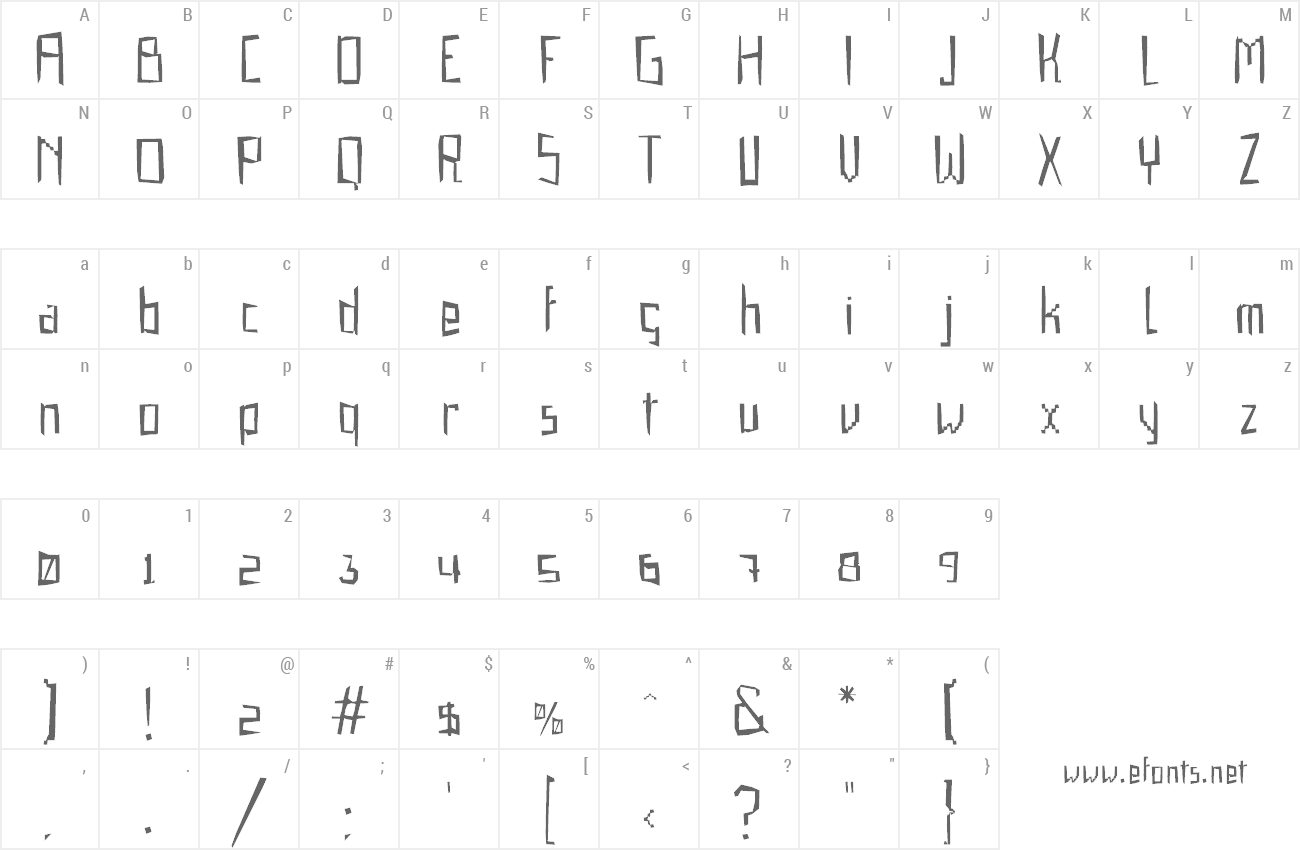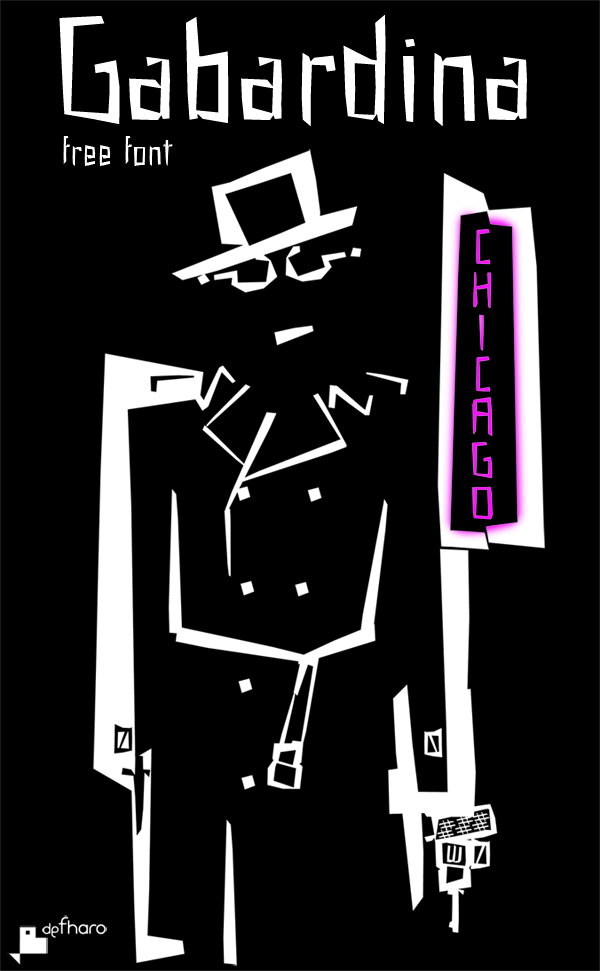
| Font name: | Gabardina |
| Author: | deFharo |
| Note by deFharo | |
| Gabardina es una font distorsionada de lineas rectas que puedes usar en carteles, posters y logotipos. Tiene funciones OpenType con nĂºmeros y ligaduras. http://defharo.com/fonts/descargar-fuentes-gratis/ |